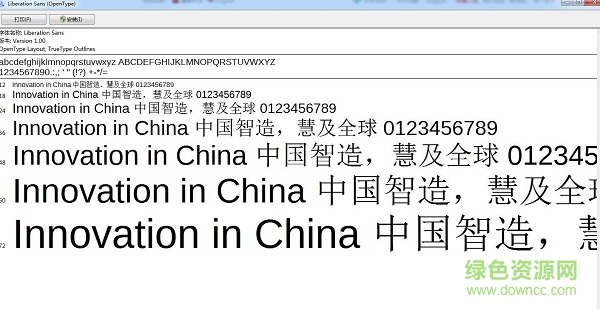
liberationsans 能顯示中文么?這套字體是microsoft office軟件上的辦公字體,包括liberation sans narrow、liberationsans bold以及l(fā)iberationsans-regular字體等,暫不支持中文顯示,有需要者歡迎在綠色資源網下載!
Liberation字體是一款MicrosoftWindows與其辦公室套裝軟件上常被使用的字體。分別與蒙納公司的Arial、ArialNarrow、TimesNewRoman、及CourierNew兼容,這些是在MicrosoftWindows與其辦公室套裝軟件上最常被使用的字體,這套字體是為了要做為上述這些字體的自由替代品而生。